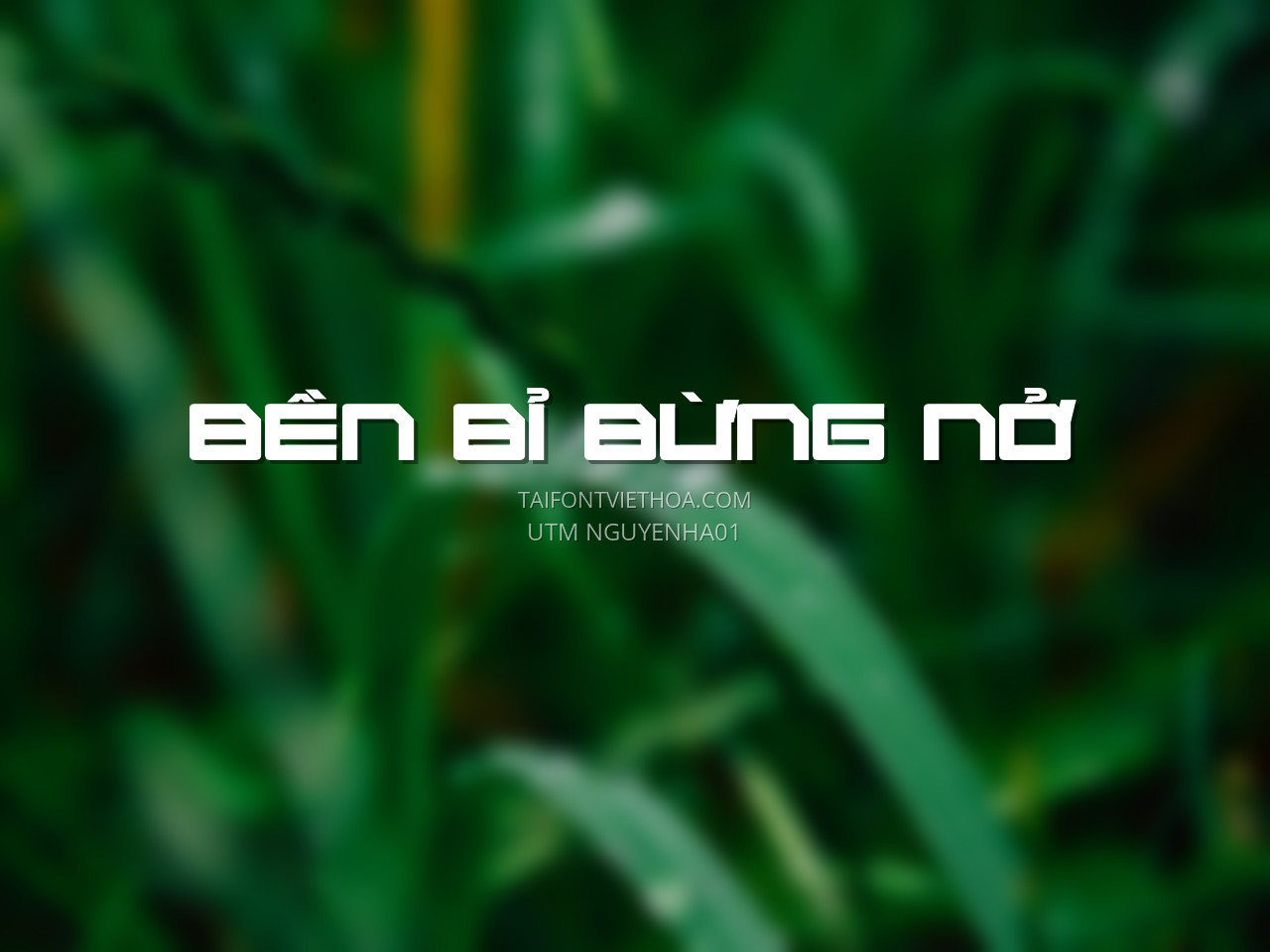
Font việt hóa UTM Nguyenha đầy đủ
Giới thiệu về font UTM Nguyenha Trọn Bộ
UTM Nguyenha Trọn Bộ là phiên bản Việt hóa của bộ font Nguyenha – một bộ sưu tập font đa dạng, bao gồm nhiều kiểu chữ khác nhau từ serif đến sans-serif, phù hợp cho nhiều mục đích thiết kế khác nhau. Bộ font này nổi bật với sự kết hợp hài hòa giữa các nét chữ truyền thống và hiện đại, mang lại sự linh hoạt và phong cách riêng biệt cho từng dự án. Phiên bản Việt hóa đã được hoàn thiện để hỗ trợ đầy đủ tiếng Việt cùng hơn 200 ngôn ngữ khác, đáp ứng nhu cầu đa dạng của cộng đồng thiết kế Việt Nam.
Đặc điểm thiết kế và ứng dụng của UTM Nguyenha Trọn Bộ
UTM Nguyenha Trọn Bộ bao gồm nhiều kiểu chữ với cấu trúc đa dạng, từ serif có chân thanh lịch đến sans-serif hiện đại. Bộ font có nhiều biến thể trọng lượng và phong cách, giúp các nhà thiết kế dễ dàng lựa chọn và kết hợp trong nhiều bối cảnh thiết kế khác nhau. Thiết kế font mang lại cảm giác chuyên nghiệp, dễ đọc và linh hoạt.
Font thích hợp sử dụng trong thiết kế sách, tạp chí, nhận diện thương hiệu, quảng cáo, bao bì sản phẩm và các dự án truyền thông đa phương tiện. Các ngành nghề phù hợp gồm: xuất bản, thời trang, công nghệ, giáo dục và quảng cáo.